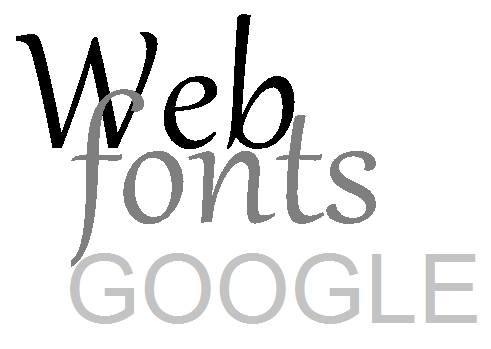
Hier möchte ich euch zeigen, wie ihr eine Google Webfont mit enqueue in ein WordPress Theme einbinden könnt.
Kurze Einleitung..
Es gibt sogenannte Serifen Schriften, wie Times New Roman und serifenlose Schriften, wie Arial. Diese beiden Namen kennt wohl jeder. Sie werden bis heute noch als sogenannte „Fallback“ Schriften zusätzlich angeführt. Viele Jahre waren diese Schriften für Browser die sogenannte Standardschriften. Alle anderen wurden einfach nicht dargestellt.
Schriften kaufen und direkt in ein WordPress Theme einbinden über @font-face ist teuer. Und es gibt die Google Webfonts. 🙂
Es gibt allerdings sowohl vom Style her , wie auch von der Ladezeit her einiges zu beachten. Was sich am besten etabliert hat:
– maximal zwei Schriftstile zu kombinieren
– nur die Schriftschnitte zu laden, welche auch tatsächlich dann verwendet
– @import Methode meiden
werden.
Tipp:
Einfach zur Inspiration mehrere Webseiten ansehen und nachsehen,
welche Schriften das sind, die einem gefallen.
So kannst du nachsehen, welche Schriften eine Webseite verwendet:
Einfach z.B. in Windows STRG U klicken. Es öffnet sich ein neues Fenster mit dem Quelltext der Webseite. Ziemlich im oberen Bereich sieht man dann schon die Google Fonts eingebunden. Wer die Webdeveloper Toolbar im Firefox aktiviert hat, der kann auch auf Extras > Erweiterung Webdeveloper >CSS > CSS ansehen gehen. Dort findet er dann über die eingebundenen Schriften noch genauere Informationen.
Google Webfonts bietet drei Möglichkeiten an, die Schriften einzubetten. Zwei davon habe ich euch hier erklärt.
Die, welche wir heute ansehen, wird von Google nicht angeboten, ist auch WordPress spezifisch. Allerdings die am ehesten zu empfehlende Methode. Dabei wird der von Google Webfonts erstellte Code einfach in die functions.php des eigenen WordPress Themes mit enqueue style eingebunden.
Zunächst möchte ich euch noch zeigen, wie man zwei Schriften gleichzeitig einbinden kann. Dazu wählen wir einmal zwei Schriftarten in den Google Webfont aus. In diesem Beispiel wähle ich Open Sans, als serifenlose Schrift und Lora, als serifen Schrift aus. Diese füge ich zu add collections hinzu.
Wähle also deine Collection aus und klicke dann rechts unten auf den Button > use. Hier kannst du noch einmal alle Schriftschnitte auswählen. Rechts siehst du den Page Speed Zeiger, der wenn du zu viele auswählst, bald auch im roten Breich sein kann. Also nur geziehlt das auswählen, was du benötigst.
Als nächstes wähle das Character Set aus. Setze das Häkchen bei Latin. Als nächstes > add this Code to your Website und zwar Standard. Beim enqueuen nur das auswählen, was ab https dort steht:
// Google Fonts kopieren 'https://fonts.googleapis.com/css?family=Lora|Open+Sans'
ACHTUNG:
Wir binden hier die Google Fonts über enqueue style in die functions.php des eigenen WordPress Themes ein. Für dein eigenes Custom WordPress Theme reicht das aus.
Falls du ein Theme zur Veröffentlichung in wordpress.org hochladen möchtest, dann befolge folgende Anleitung : How to add Google fonts to WordPress themes
Öffne nun die functions.php deines Themes und füge folgenden Code hinzu. Tausche den Link – das https… – mit deinem eigenen aus.
<?php
function mdq_add_google_fonts() {
wp_enqueue_style( 'mdq-google-fonts',
'https://fonts.googleapis.com/css?family=Lora|Open+Sans', false );
}
add_action( 'wp_enqueue_scripts', 'mdq_add_google_fonts' );
?>
Weitere Quellen bei wpbeginner. Ein weiterer guter Beitrag, m.E. obwohl schon älter, ist hier < using google webfonts with wordpress.. In diesem Beitrag sind in den Kommentaren viele gute Antworten, warum eigentlich Google Webfonts etc.
Ebenfnalls ein guter Tipp ist im webdesign-journal.de, wo viele Schriftpaar -beispiele vorgestellt werden. Ebenfalls gibt es eine neue Version der Google Fonts. Zur Zeit wirst du gefragt, ob du die neue Version verwenden möchtest. Sie sieht ehrlich super aus. Allerdings muss man sich ein wenig Zeit nehmen um sich alles anzusehen.
FAZIT:
Falls das Thema Webfonts für dich noch neu ist und du ein wenig experimentieren möchtest, wie du die Fonts einbinden kannst, dann sind diese Tipps hier hoffe ich, hilfreich.
Ich persönlich habe bis jetzt immer nur die Standardschriften verwendet. Sie funktionieren, man hat keine Arbeit und der Page Speed stimmt auch. Allerdings sind Schriften schon etwas ganz besonderes und man kann mit Schriften einem Webauftritt einen ganz neuen, speziellen Charakter verleihen.
Learnin by doing, sowie vom groben zum feinen.
In diesem Sinne, denke ich, sollte man sich um den Page Speed erst in zweiter Linie Gedanken machen und eben nur geziehlt auswählen, was man benötigt.